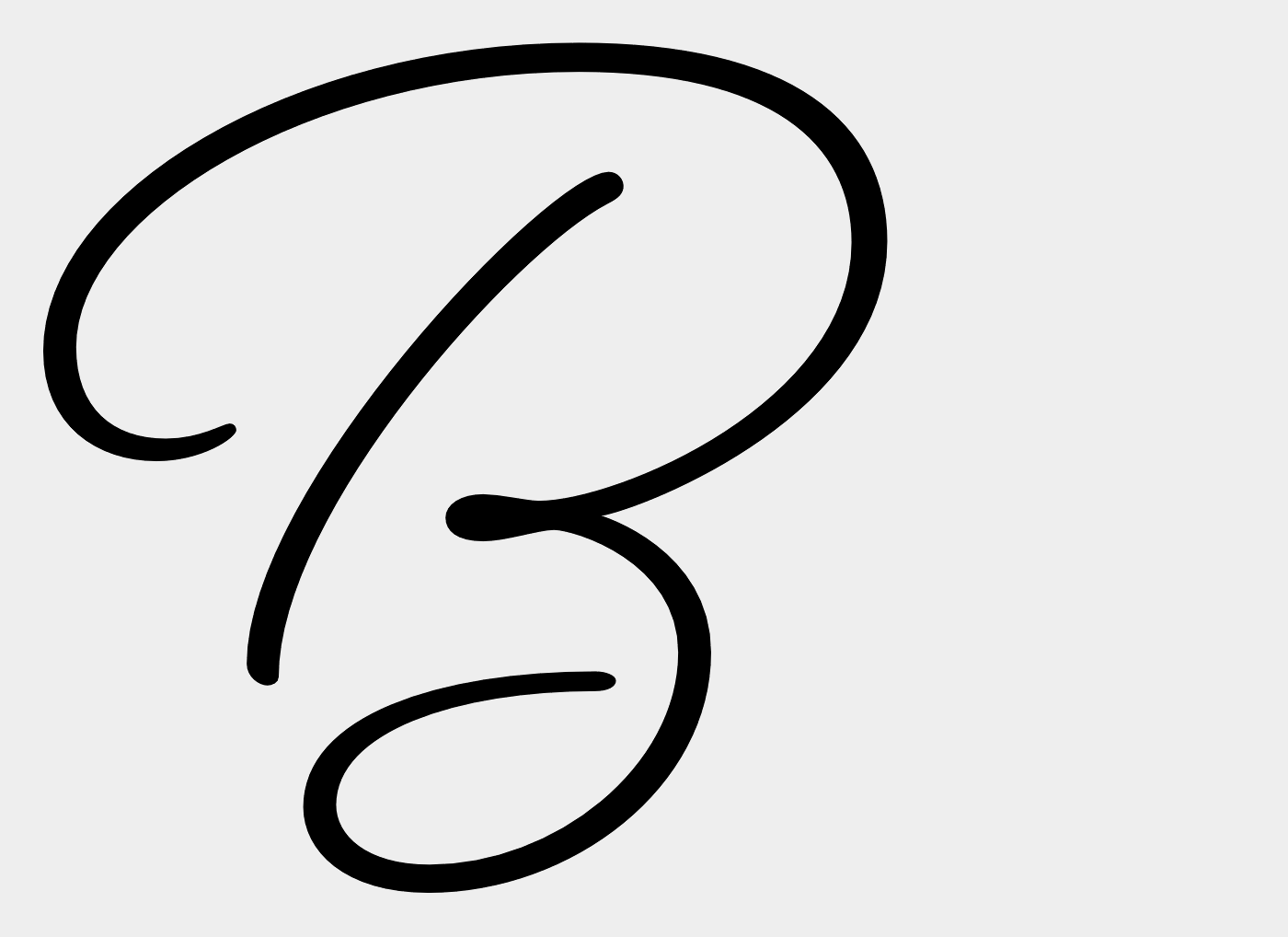
ich brauche bitte eure Hilfe. Nach 371 Tagen ist meine Tochter Bente im September verstorben. Als Erinnerung würde ich gern ein großes B herstellen lassen. Es soll Schreibschrift sein und mit einem großen Bogen unten auslaufen. Ich kann hierzu leider nichts finden. Hat jemand einen Rat oder Tipp für mich.
Kannst Du etwas genauer beschreiben, wie das Versal-B aussehen soll und welche praktischen Anforderungen erfüllt werden müssen? Soll es stehen können? Soll es an die Wand gebracht werden?
Muss es zwingend aus einer Schreibschrift erzeugt werden?
Ob ihr Experten es Schreibschrift nennt ist mir nicht klar. Es soll ein großes geschwungenes B sein... ruhig kräftig ... und der untere Bogen soll gerade nach links unten auslaufen. Wie ich es nachher plastisch darstellen werden, weiß ich noch nicht 100prozig. Sicher in Holz und als Erinnerung auf meinen Arm. Der Rest wird sich zeigen...
Wenn es Schreibschrift sein soll, bin ich immer ganz schnell bei Laura Worthington. Sie macht sehr schöne, gefühlvolle Schreibschriften. Da bin ich auf die Beloved gestoßen:
Kräftig und nach links unten auslaufen vielleicht sowas:
Wenn es gefräst, gelasert etc. werden soll, müssten die Pfade verbunden sein. Ansonsten auf einer Grundlage montieren. Das wäre aber nicht so charmant wie ein freistehender Buchstabe. Wenn Du es gerne mal in den Arm und Hände nehmen willst, sollten die Kanten gerundet sein, so ein Wonneproppen ist ja auch weich und rund ...
Zu der Buchstabensuche: Ich weiß noch nicht genau, was genau gesucht wird, daher hier ein paar Eingrenzungsversuche. Neben Laura Worthington ist auch Rob Leuschke ein begabter Schreibschriftdesigner.  Da würde ich folgende ins Auge fassen:
Weitere Schreibschriften, die passen könnten:
Love Light ROB (die passt zwar nicht ganz in die Anforderung, würde aber uU wegen der Details passen)
Die gibt es auch unter dem Namen Ruthie ohne Herzchen und auch beim Eichhörnchen …
hier noch ganz was anderes: die eclat.
bogen geht zwar oben weg, dafür schön kräftig, weich und rund: BaBy-haft